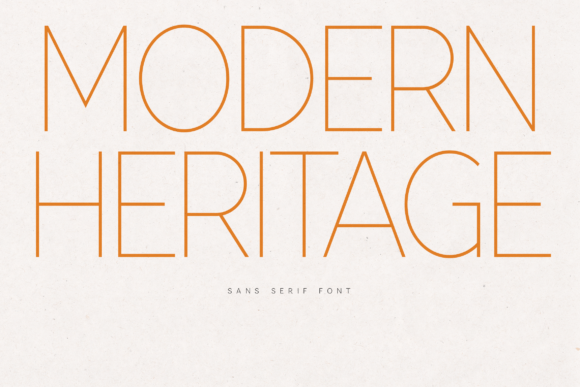
Modern Heritage
Modern Heritage : critique détaillée d’une police de caractère raffinée
Si vous recherchez une typographie qui allie minimalisme moderne et élégance intemporelle, Modern Heritage répond parfaitement à ces exigences. Conçue comme une sans‑serif mince aux traits délicats et à l’espacement généreux, elle se distingue dans les projets de luxe, les mises en page éditoriales et le design contemporain.
Pourquoi choisir Modern Heritage ?
- Esthétique sophistiquée : les lignes fines offrent une impression de légèreté tout en conservant une présence visuelle forte.
- Lisibilité optimale : l’espacement généreux entre les caractères garantit une clarté exceptionnelle, même à petite taille.
- Polyvalence haut de gamme : idéale pour le branding de marques premium, les magazines de mode, les catalogues de produits de luxe et les sites web au design épuré.
- Identité moderne : son style minimaliste crée une identité visuelle contemporaine, parfaite pour les startups innovantes et les projets créatifs.
- Compatibilité multilingue : prend en charge les jeux de caractères étendus, ce qui la rend adaptée aux contenus internationaux.
Points forts de la conception
Modern Heritage se caractérise par des strokes subtils qui apportent une touche de finesse sans compromettre la robustesse du texte. L’équilibre entre les largeurs de caractères et les interlignes crée une harmonie visuelle qui attire l’œil tout en facilitant la lecture prolongée.
Cas d’utilisation recommandés
- Logos et identité de marque pour le secteur du luxe.
- Mises en page éditoriales (magazines, catalogues, livres d’art).
- Web design de sites haut de gamme, portfolios créatifs et landing pages minimalistes.
- Supports marketing premium (brochures, cartes de visite, packaging).
Conclusion
En résumé, Modern Heritage est bien plus qu’une simple police sans‑serif : c’est une déclaration de style qui combine subtilité et puissance visuelle. Que vous soyez une marque de luxe, un éditeur exigeant ou un designer cherchant la clarté moderne, cette police vous offrira la distinction et la cohérence nécessaires pour démarquer vos projets.